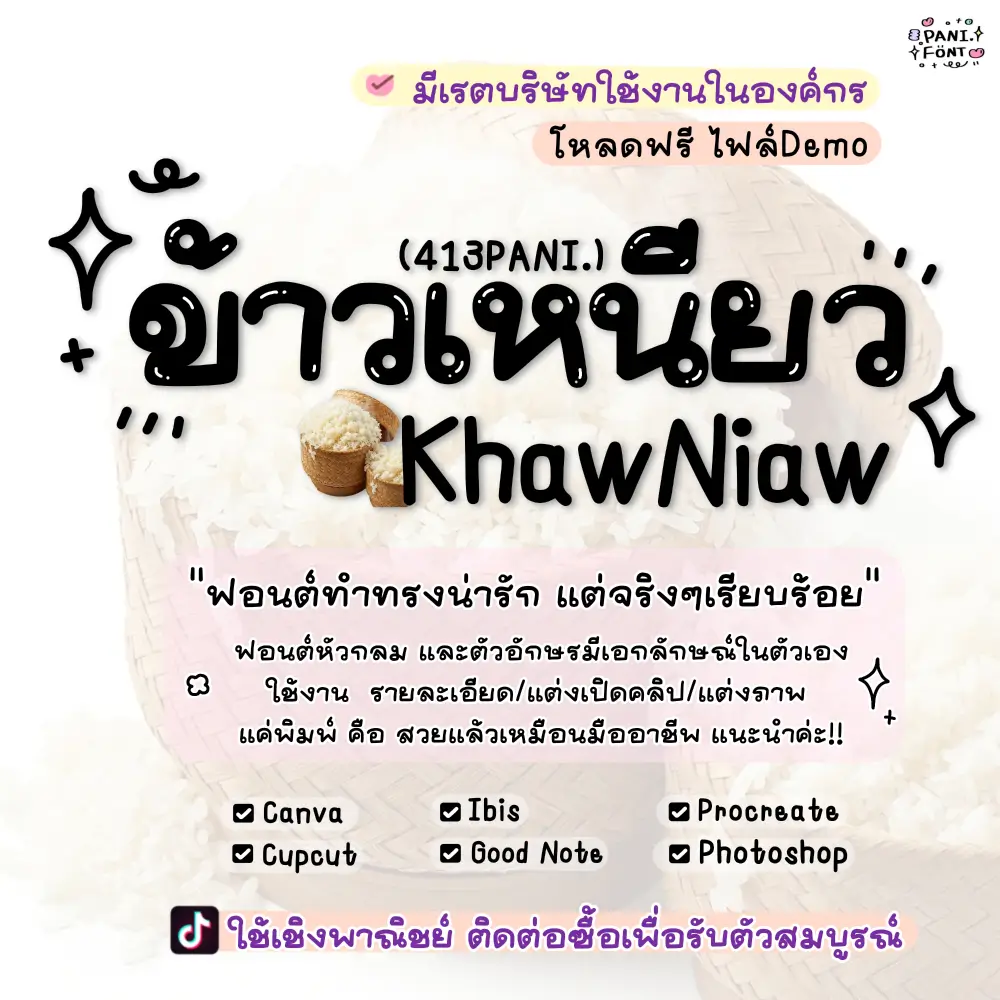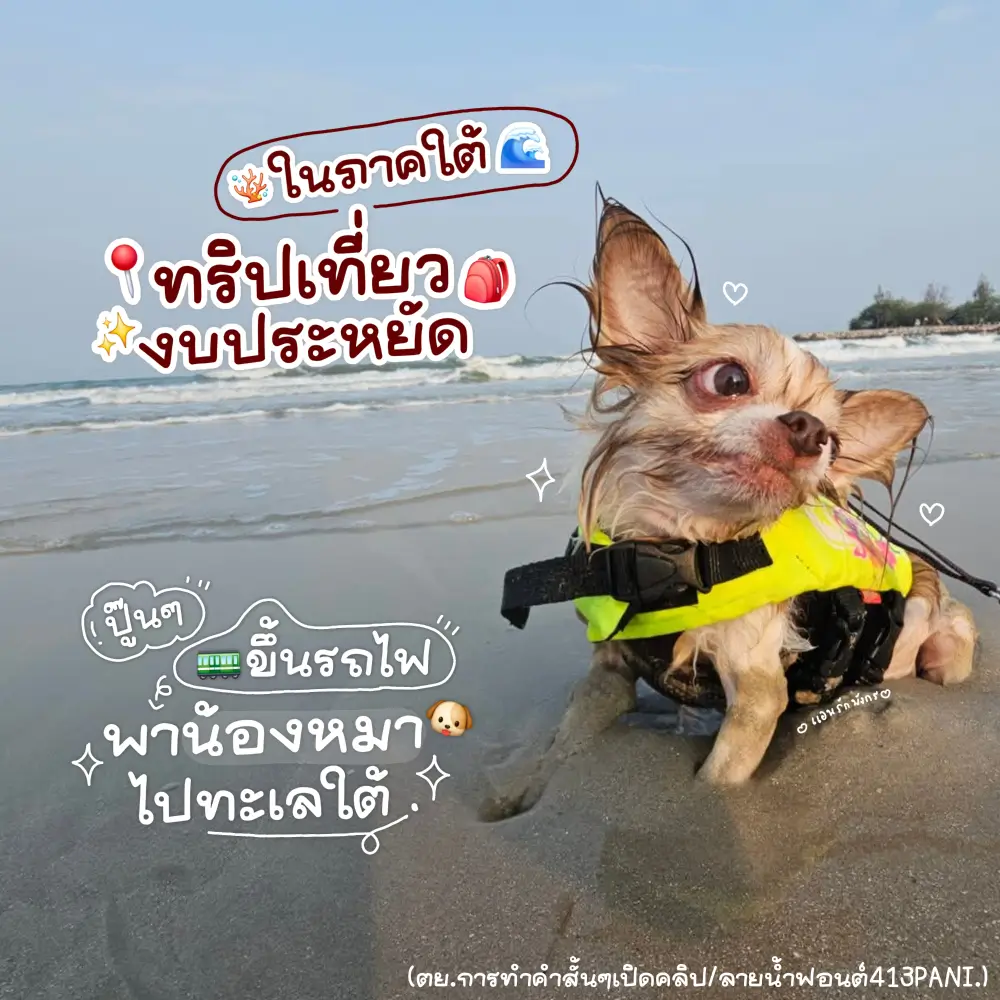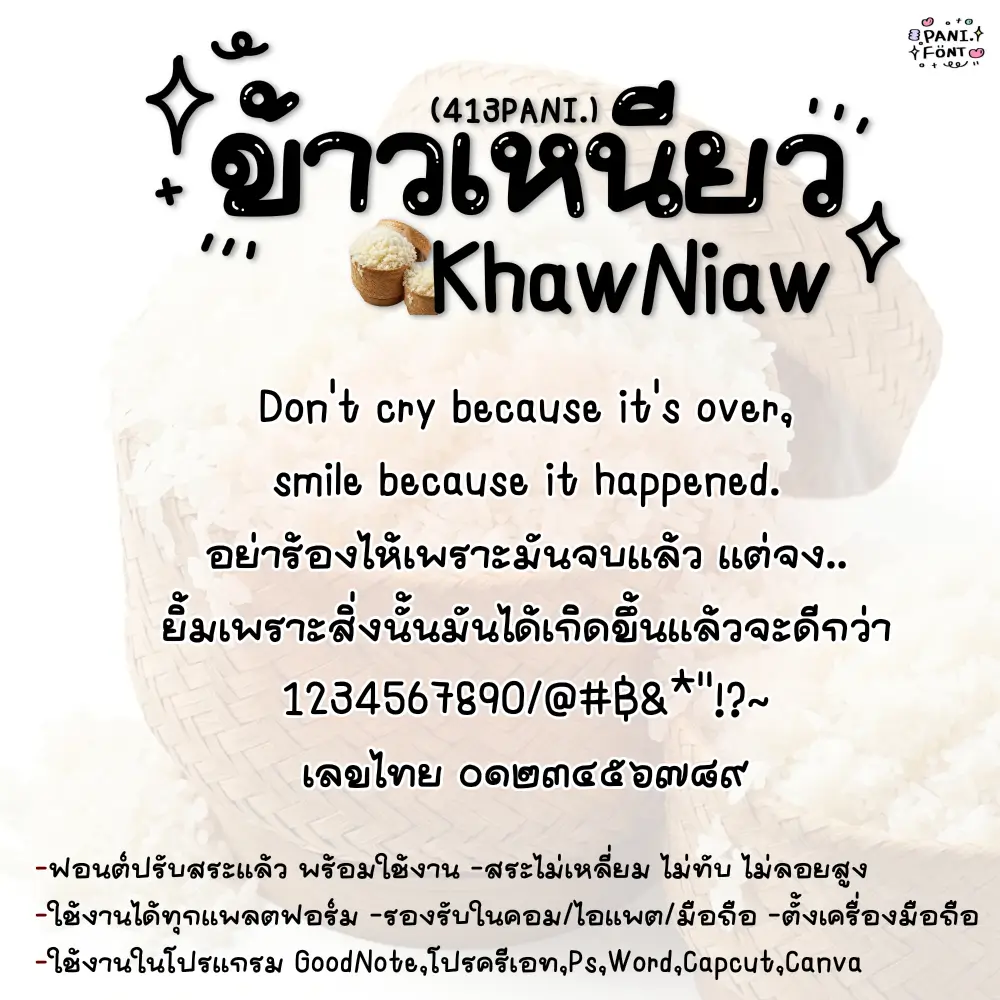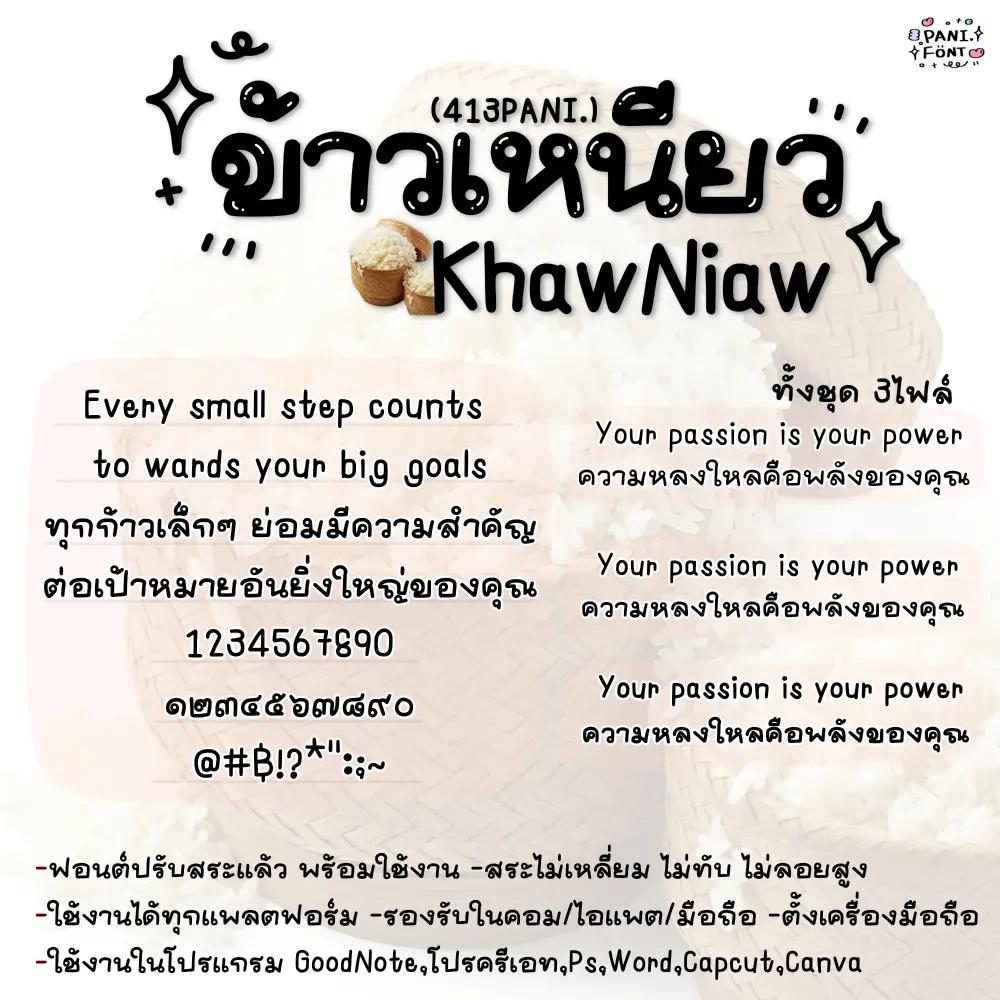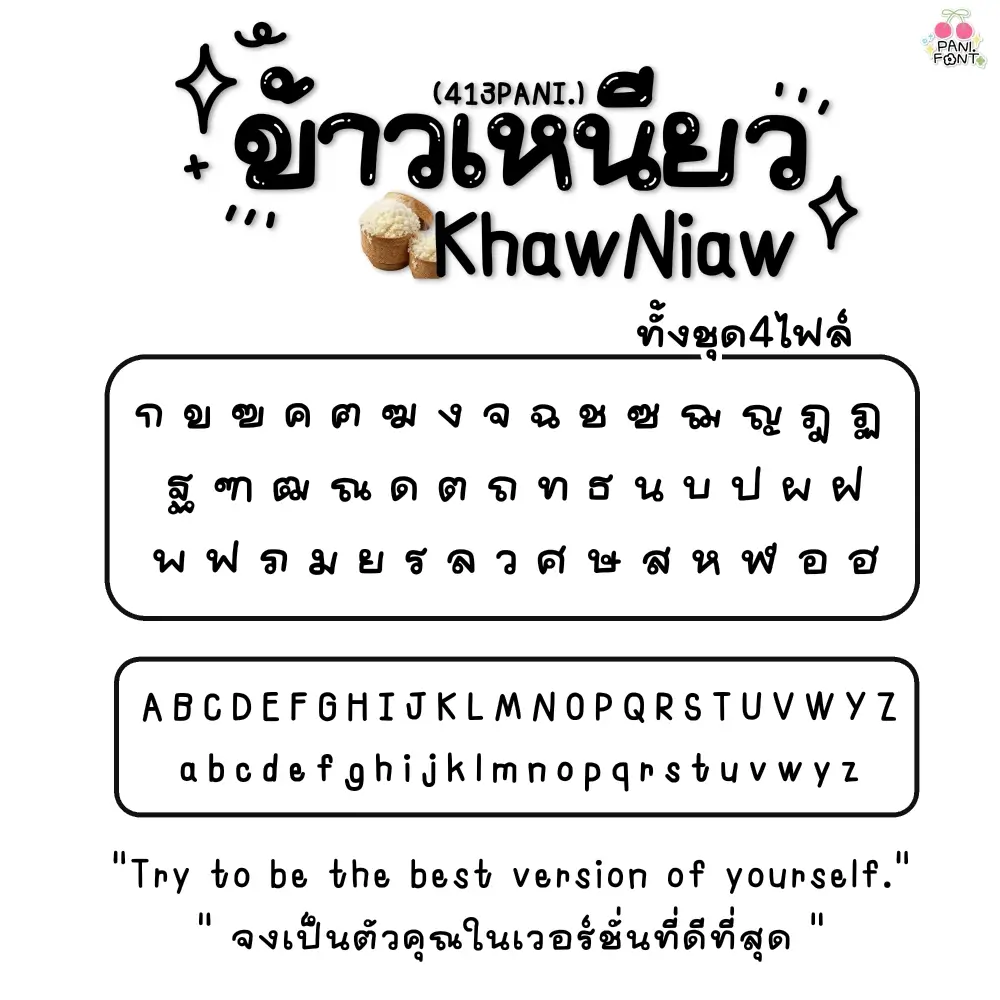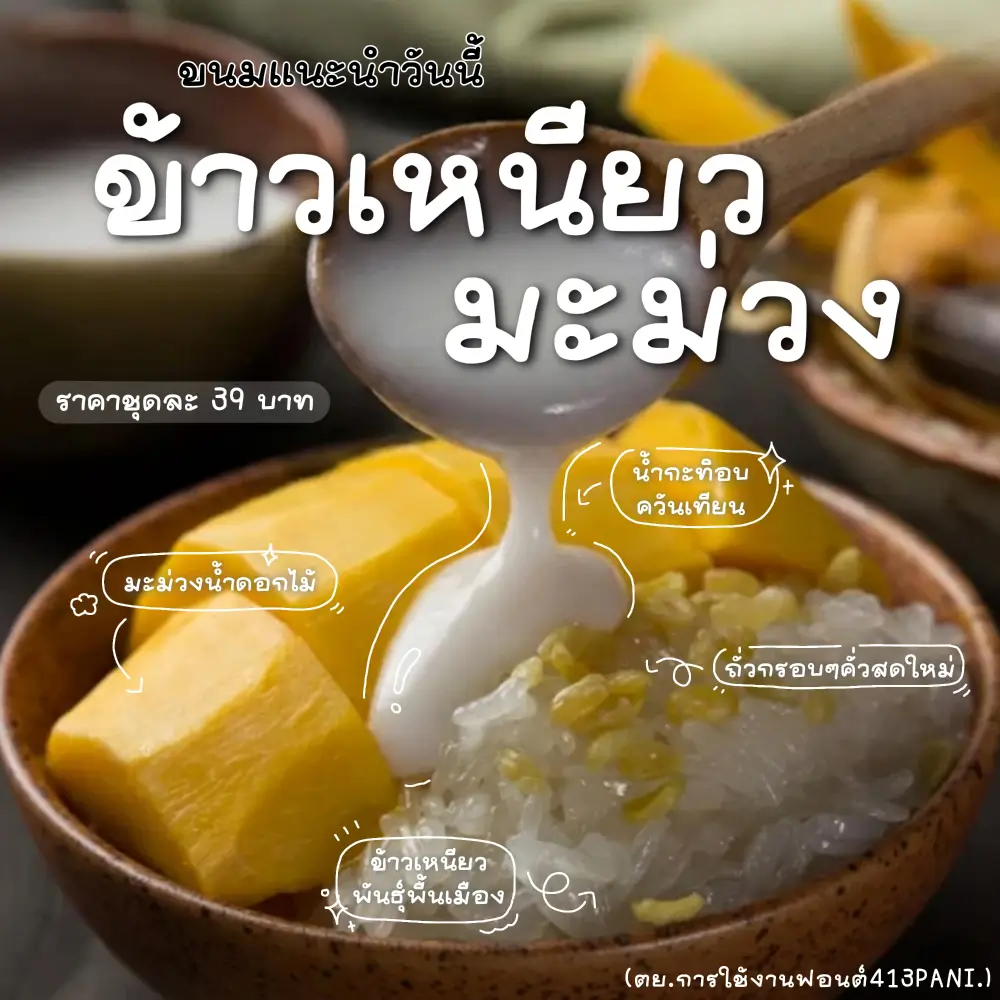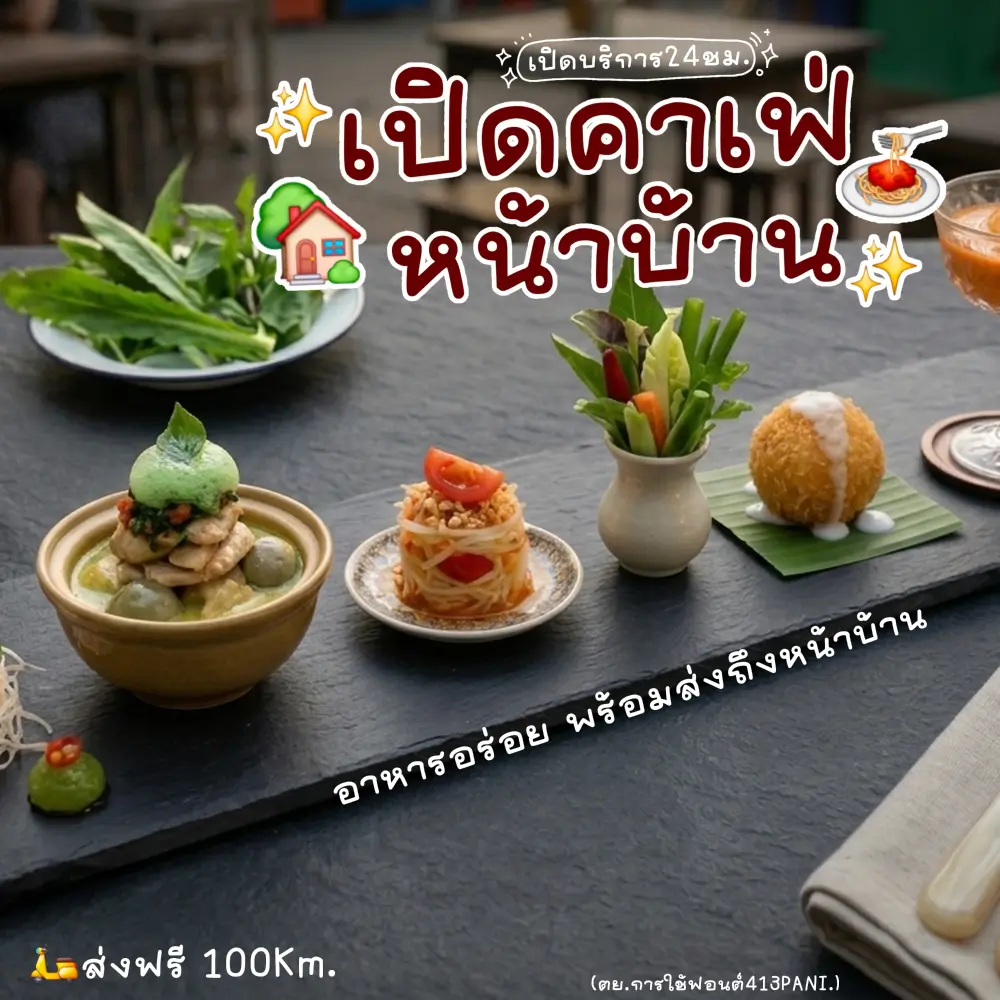
PANI.413ข้าวเหนียว
ฟอนต์ PANI.413ข้าวเหนียว – ฟอนต์ทำทรงน่ารัก แต่จริงๆ เรียบร้อย หัวกลม และตัวอักษรมีเอกลักษณ์ในตัวเองการใช้งาน จะแต่งเปิดคลิป รึแต่งภาพ แค่พิมพ์ คือ สวยแล้วเหมือนมืออาชีพ แนะนำค่ะ!!